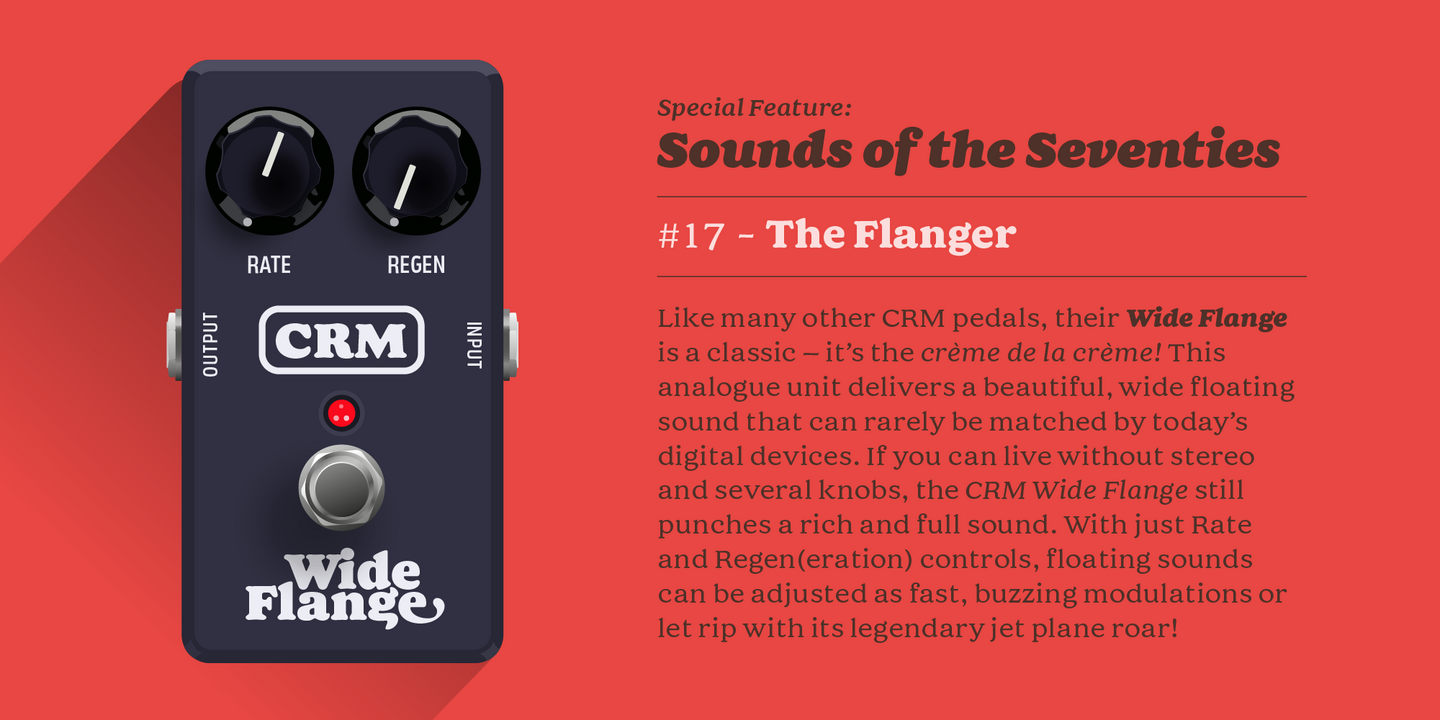
Fonts von Paulo Goode.
Paulo hatte eine lange und abwechslungsreiche kreative Laufbahn hinter sich, bevor er sich 2014 an das Schriftdesign wagte. Bei der Gestaltung von Schriften greift er auf seine 30-jährige Erfahrung als technischer Illustrator, Grafikdesigner und Webseite Designer/Entwickler zurück. Als Schriftgestalter weiß er genau, worauf es bei der Gestaltung von Nutzer ankommt. Paulos Veröffentlichungen konzentrieren sich hauptsächlich auf Schriften für Branding-Zwecke.
Kühn dem Namen nach, kühn der Natur nach. Sie ist möglicherweise "The Greatest Schrift of All Time". Natürlich ist das nur ein Scherz, aber diese schrullige, selbstbewusste und liebenswerte Serifenschrift Schrift hat eine starke Präsenz, die Überschriften dominiert und Ihren Texten eine besondere Note verleiht.
Cream ist eine weiche Serifenschrift Schrift , die von Oswald Bruce Coopers gleichnamiger Schriftfamilie inspiriert wurde, die von 1918 bis 1924 entworfen wurde. Ich bin mir sicher, dass Sie den Einfluss sofort erkennen können, aber Cream hat ihren eigenen, einzigartigen Geschmack. Ich habe versucht, eine einheitlichere und ausgewogenere Schrift zu erreichen, die glattere Kurven und konsistentere Linien hat - zusammen mit einer Fülle von nützlichen Funktionen.
Die Majesty wurde mit der Absicht entworfen, jeder Anwendung einen Hauch von edler Klasse zu verleihen. Majesty ist eine eingeschnittene Schrift, die eine freundliche Resonanz hat, ohne zu streng zu sein. Sie ist zwischen den Schriftfamilien Trajan und Albertus angesiedelt und wurde von der jahrhundertealten Tradition der gravierten Schriften inspiriert.
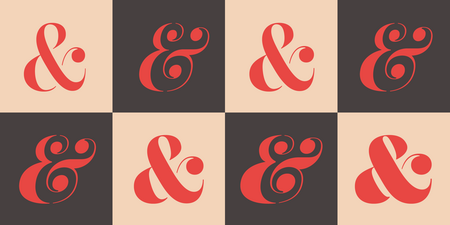
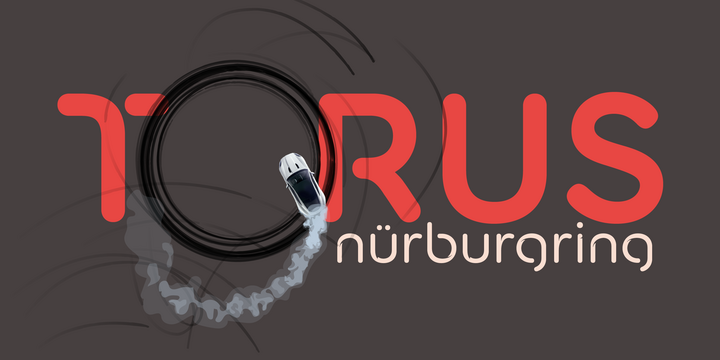
Paulo Goode
Als Kind war ich fasziniert von der Vielzahl der Buchstabenformen, die uns umgeben, und ich verbrachte Stunden damit, Wörter (und Autos) in meine Skizzenbücher zu zeichnen. Ich weiß nicht, was aus diesen Skizzen geworden ist, aber als Autodesigner habe ich es jedenfalls nie geschafft! Vielleicht hat mein Fonts mehr Erfolg? Als ich erwachsen wurde, entwickelte ich meine künstlerischen Fähigkeiten weiter, wurde technischer Illustrator und wechselte mit dem Aufkommen des Macintosh-Computers ins Grafikdesign. Im Alter von 45 Jahren entdeckte ich mein Interesse an der Gestaltung von Schrift wieder und verliebte mich in den Prozess der Erstellung von Font und der Produktion einiger interessanter Schriften von Rang. Ich bin immer noch fasziniert von der Vielzahl an Buchstabenformen, die uns umgeben, und freue mich sehr, dass ich meine eigene beisteuern kann.